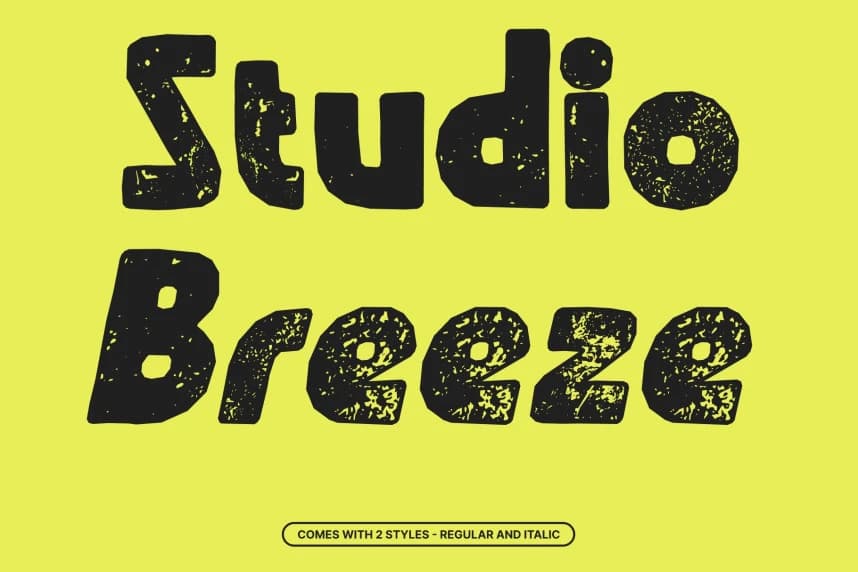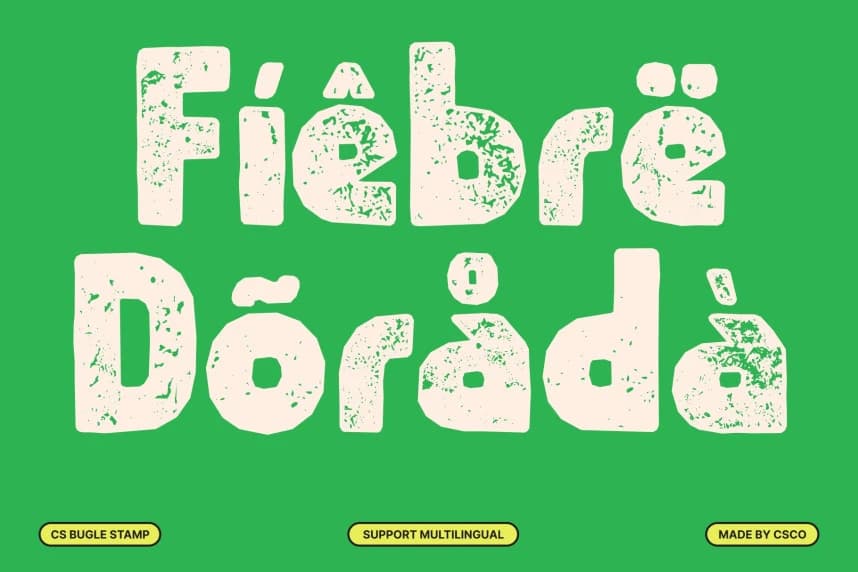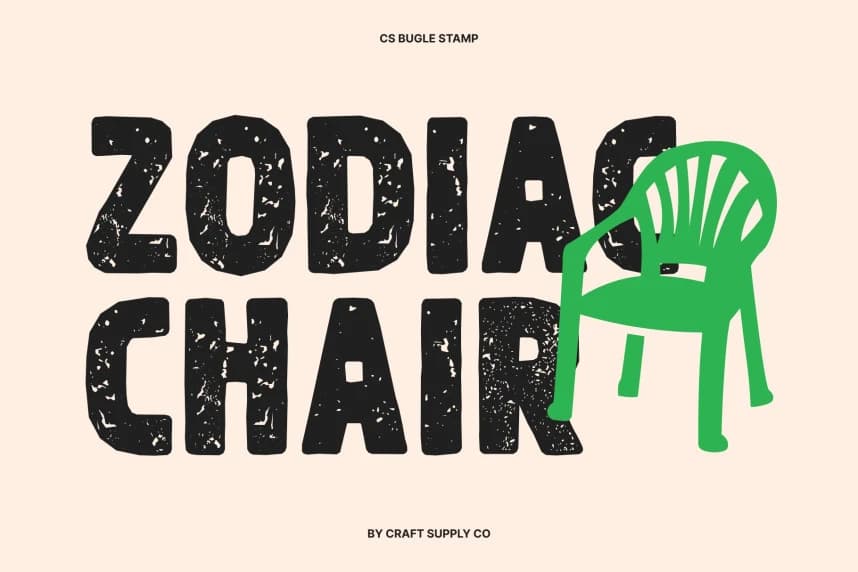
CS Bugle Stamp Yazı Tipi
CS Bugle Stamp Font – Tekstüre Sahip 80'ler Enerjisiyle Retro Kalın Yazı Tipi; Klasik 80'ler Estetiğini Modern Bir Dokunuşla Birleştirir. Bu, 1980'ler tasarımının canlı ruhunu yakalayan kalın bir sans-serif yazı tipidir.
CS Bugle Stamp Font – Dokulu 80'ler Enerjisiyle Retro Kalın Yazı Tipi, Klasik 80'ler Estetiğine Modern Bir Dokunuş. Bu, 1980'lerin tasarımının canlı ruhunu yakalayan kalın bir sans-serif yazı tipidir.